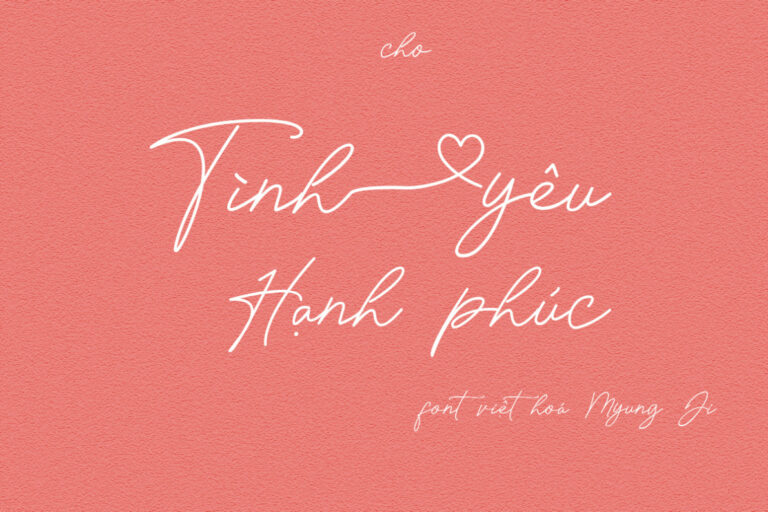
Trong thế giới thiết kế đồ họa ngày nay, việc tìm kiếm một Font Chữ độc đáo và ý nghĩa luôn là một nhiệm vụ quan trọng để tạo nên sự khác biệt. Đặc biệt, với những ai đang tìm kiếm sự lãng mạn, nhẹ nhàng và một chút bay bổng, Font việt hoá MJ LoveLy Love chính là lựa chọn không thể bỏ qua. Đây không chỉ là một font chữ thông thường mà còn là một tác phẩm nghệ thuật, mang đến cảm xúc và cá tính riêng biệt cho từng dự án. Font này được nhiều nhà thiết kế yêu thích bởi sự mềm mại, uyển chuyển, rất phù hợp cho các thiết kế liên quan đến tình yêu, sự kiện đặc biệt hay đơn giản là tạo điểm nhấn ngọt ngào cho các ấn phẩm.
Khám Phá Sức Hút Của Font việt hoá MJ LoveLy Love Trong Thiết Kế
Font việt hoá MJ LoveLy Love nổi bật với phong cách viết tay mềm mại, các đường nét được trau chuốt tỉ mỉ, tạo cảm giác thân thiện và gần gũi. Sự kết hợp giữa nét thanh và nét đậm một cách hài hòa giúp font chữ này dễ dàng thu hút ánh nhìn ngay từ lần đầu tiên. Điểm đặc biệt của font là khả năng truyền tải cảm xúc mạnh mẽ, từ sự đáng yêu, ngọt ngào đến nét lãng mạn, bay bổng. Đây là lý do vì sao nó trở thành lựa chọn hàng đầu cho thiệp cưới, thiệp mời sinh nhật, poster sự kiện tình yêu, hay thậm chí là bìa sách, tạp chí có chủ đề lãng mạn. Với khả năng tương thích cao trên nhiều phần mềm thiết kế như Photoshop, Illustrator hay Canva, MJ LoveLy Love giúp các nhà thiết kế dễ dàng sáng tạo mà không gặp bất kỳ trở ngại nào về kỹ thuật.
Đặc Điểm Nổi Bật Của MJ LoveLy Love Việt Hóa
Phiên bản việt hóa của MJ LoveLy Love đã được các nhà phát triển tối ưu để hỗ trợ đầy đủ các ký tự tiếng Việt, bao gồm cả dấu thanh và các ký tự đặc biệt, đảm bảo tính thẩm mỹ và dễ đọc khi sử dụng trong ngữ cảnh tiếng Việt. Điều này đặc biệt quan trọng vì nếu một font chữ đẹp mà không hỗ trợ tiếng Việt đầy đủ, nó sẽ mất đi rất nhiều giá trị khi áp dụng vào các dự án tại Việt Nam. Sự cẩn thận trong quá trình việt hóa giúp MJ LoveLy Love giữ nguyên được tinh thần lãng mạn, bay bổng của bản gốc, đồng thời mở rộng khả năng ứng dụng cho vô số mục đích khác nhau. Các nét chữ được thiết kế tinh tế, không bị lỗi khi gõ dấu, mang lại trải nghiệm sử dụng mượt mà và chuyên nghiệp. Nó thực sự là một tài sản quý giá cho bất kỳ ai hoạt động trong lĩnh vực sáng tạo.
Ứng Dụng Đa Dạng Của Font việt hoá MJ LoveLy Love
Với vẻ đẹp độc đáo của mình, Font việt hoá MJ LoveLy Love có thể được ứng dụng vào rất nhiều lĩnh vực khác nhau. Trong ngành cưới hỏi, nó là lựa chọn hoàn hảo cho việc thiết kế thiệp mời, banner trang trí hay các ấn phẩm kỷ niệm. Đối với các cửa hàng kinh doanh sản phẩm handmade, đồ trang sức hay các món quà tặng, font chữ này sẽ giúp tạo ra một thương hiệu thân thiện, ấm áp và đầy cá tính. Các blogger hay vlogger cũng có thể sử dụng MJ LoveLy Love để thiết kế logo, tiêu đề video hoặc hình ảnh thumbnail, thu hút người xem bằng sự ngọt ngào và lãng mạn. Ngay cả trong việc thiết kế bao bì sản phẩm, nhãn mác, hay các ấn phẩm quảng cáo, font chữ này cũng thể hiện được sự linh hoạt và khả năng biến hóa tuyệt vời, tạo ra dấu ấn khó quên trong lòng khách hàng.
Hơn nữa, trong các dự án cá nhân, việc sử dụng font này để viết nhật ký điện tử, tạo hình ảnh quote truyền cảm hứng, hay thiết kế thiệp chúc mừng cho người thân, bạn bè cũng sẽ mang lại giá trị cảm xúc rất lớn. Nó giúp những thông điệp trở nên chân thành và sâu sắc hơn. Sự đa năng của MJ LoveLy Love không chỉ giới hạn ở các dự án lớn mà còn tỏa sáng trong từng chi tiết nhỏ nhất, mang đến vẻ đẹp tinh tế và sự chuyên nghiệp cho mọi tác phẩm.
Lời Khuyên Để Tối Ưu Hóa Sử Dụng Font MJ LoveLy Love
Để tận dụng tối đa vẻ đẹp của Font việt hoá MJ LoveLy Love, bạn nên kết hợp nó với các font chữ đơn giản, không chân (sans-serif) hoặc có chân (serif) cơ bản để tạo sự cân bằng. Điều này giúp phần nội dung chính dễ đọc hơn, trong khi MJ LoveLy Love làm nhiệm vụ tạo điểm nhấn hoặc tiêu đề. Tránh sử dụng font này cho các đoạn văn bản dài vì đặc tính viết tay có thể làm giảm khả năng đọc. Thay vào đó, hãy dùng nó cho các cụm từ ngắn, câu slogan, logo hoặc các tiêu đề phụ mà bạn muốn tạo ấn tượng mạnh mẽ. Sự tương phản về kích thước và màu sắc cũng là yếu tố quan trọng giúp font chữ này phát huy hết vẻ đẹp lãng mạn của mình. Một chút sáng tạo trong cách phối hợp sẽ mang lại hiệu quả bất ngờ cho tác phẩm của bạn.
Tóm lại, Font việt hoá MJ LoveLy Love không chỉ là một lựa chọn tuyệt vời cho những ai yêu thích sự lãng mạn và bay bổng trong thiết kế, mà còn là một công cụ mạnh mẽ giúp bạn truyền tải thông điệp một cách chân thành và đầy cảm xúc. Với khả năng hỗ trợ tiếng Việt hoàn chỉnh và vẻ đẹp độc đáo, font chữ này chắc chắn sẽ là một tài sản quý giá trong bộ sưu tập Font Chữ của mọi nhà thiết kế, từ nghiệp dư đến chuyên nghiệp. Hãy để MJ LoveLy Love thổi một luồng gió mới vào các dự án của bạn, mang đến sự tinh tế, ngọt ngào và một phong cách riêng không thể nhầm lẫn.